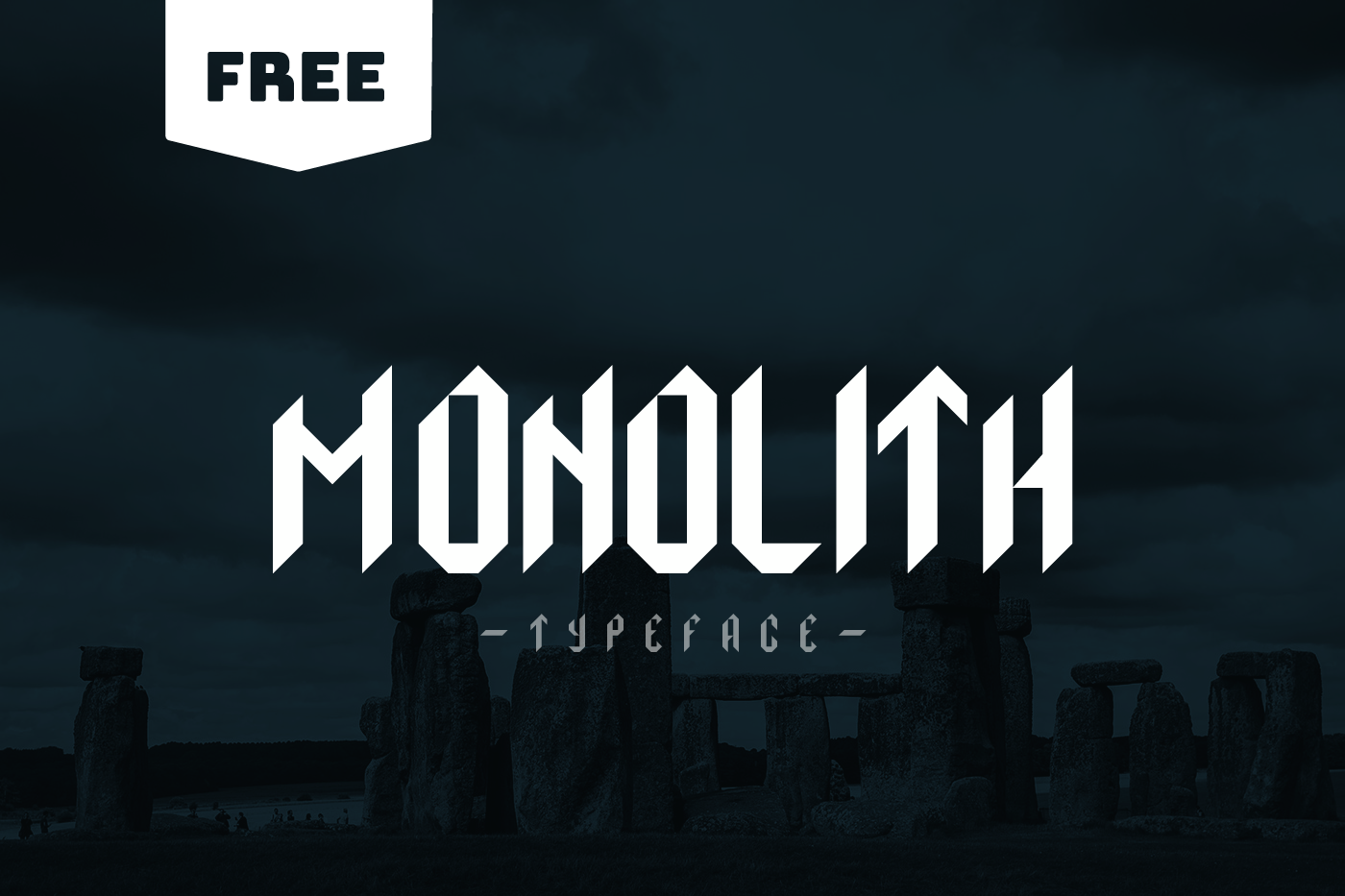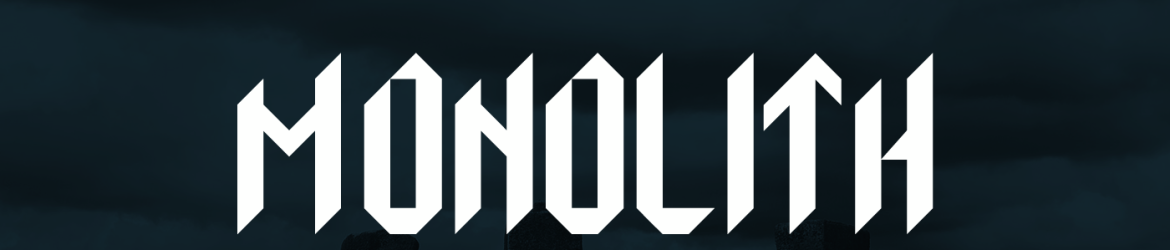
Monolith Display Typeface – Download Grátis
A Monolith é uma fonte geométrica inspirada na Blackletter disponível gratuitamente tanto para uso pessoal quanto comercial. Esta elegante tipografia não apenas captura a essência do estilo Blackletter, mas também adiciona um toque de modernidade e geometria pura à sua identidade visual. Com linhas fortes e formas claramente definidas, a Monolith é perfeita para uso em aplicações onde você deseja destacar seu conteúdo de forma única e sofisticada. Seja para criar uma aparência medieval ou incorporar um toque moderno no seu design, esta fonte oferece o equilíbrio preciso entre clássico e contemporâneo que tanto os designers quanto os amantes do bom design buscam. Com a Monolith, suas criações podem ganhar um toque único, proporcionando ao seu projeto uma identidade visual atraente e duradoura.